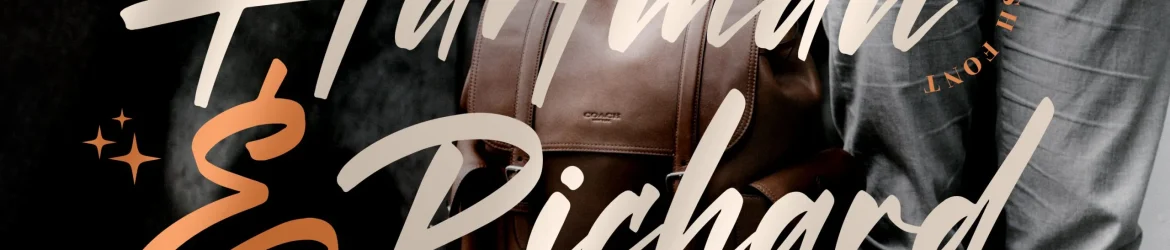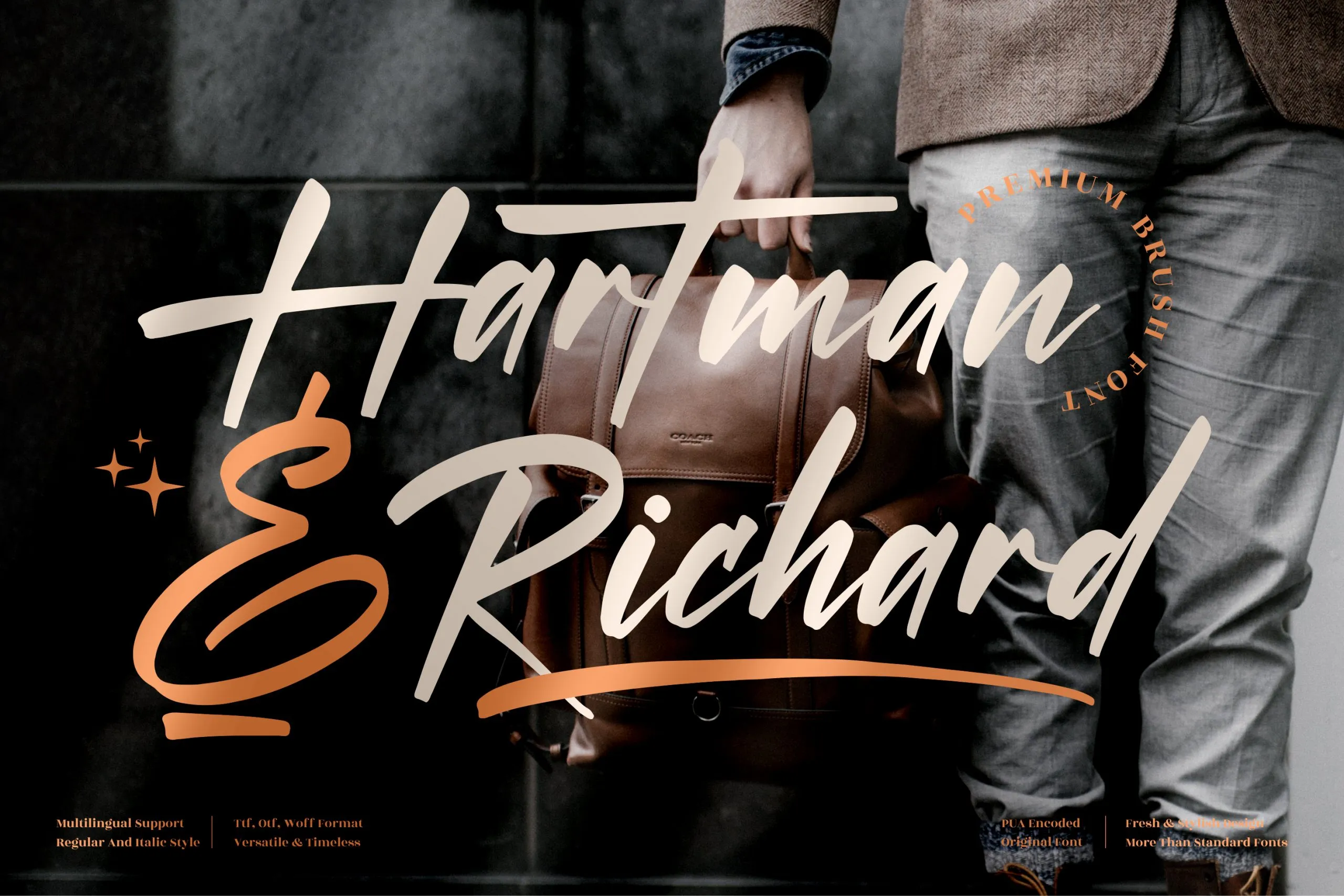
Hartman & Richard Font
Hartman & Richard é uma elegante fónt que perfila-se como um recurso incomparável para designers amadores e profissionais do design. Criado pela perspectype Studio, esta fónt premium foi desenvolvida com o intuito de trazer um toque sofisticado a qualquer projeto gráfico. Suas linhas modernas e arredondadas permitem uma expressão fluida que se adaptará perfeitamente para uma ampla variedade de aplicações: desde logotipos e embalagens, até cartões de visita e até mesmo selos em papel ou vinil. Hartman & Richard é a escolha certa para criar um design único e impecável. Seja na hora de projetar um lindo nome card, uma mensagem inspiradora sobre sua t-shirt ou mesmo um catálogo luxuoso de livros, essa fónt oferece o acabamento perfeito para suas obras finas. A perspectype Studio produziu Hartman & Richard não apenas como uma fonte, mas também como a pedra angular de todos os seus projetos de design gráfico moderno e sofisticado.